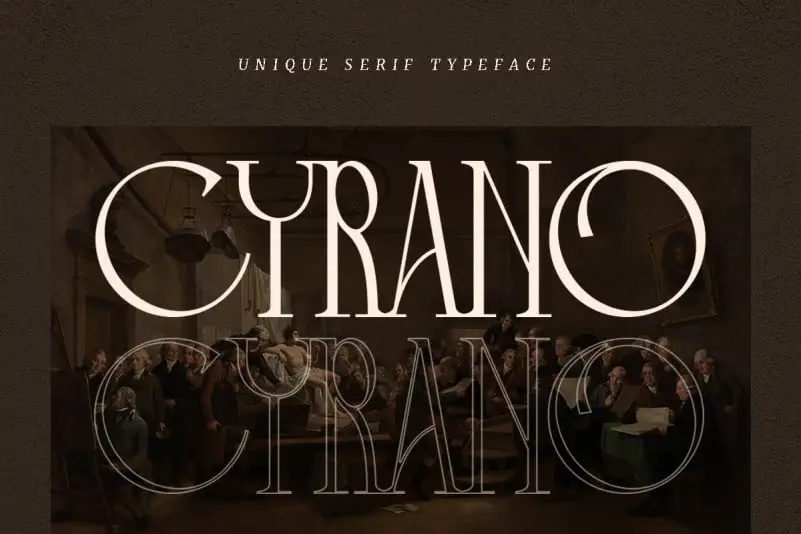
Cyrano Serif Font – Download Grátis
A Cyrano Serif Font é uma nova adição para colecionadores e designers digitais, oferecendo uma mistura moderna e refinada entre serif e sans-serif. Este tipo de letra mantém a elegância dos textos tradicionais enquanto se atualiza ao arrematar linhas curvadas contemporâneas e vintage que dão um aspecto sofisticado a quase qualquer entrelaçamento. Ideal para headlines, esta fonte única em seu gênero é perfeita para quem busca uma mistura de estilo clássico com visuais modernos. Ela foi projetada por dharmas e disponibilizada pela 99designs. Os detalhes meticulosamente criados nos caracteres garantem um texto atraente, cheio do sabor europeu que tanto apreciamos em nossa comunicação visual. Descubra mais sobre esta fonte única e inspire-se ao criar designs incríveis com ela.